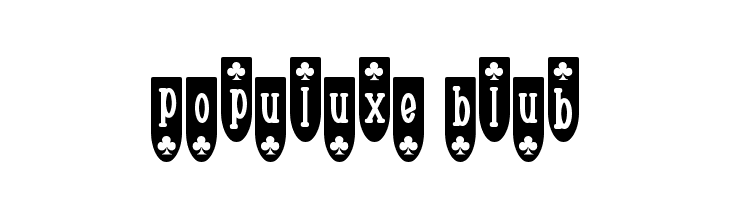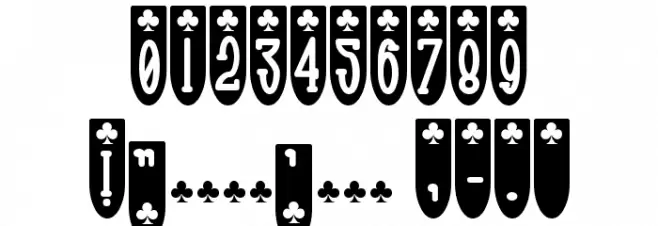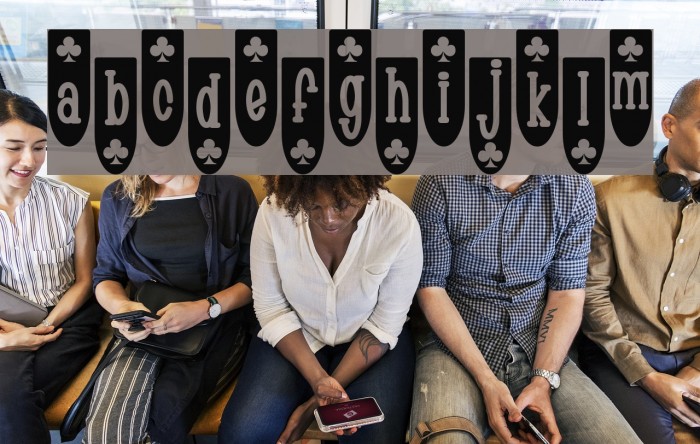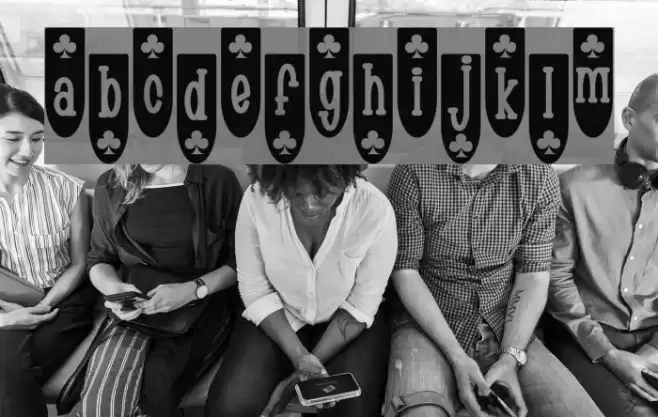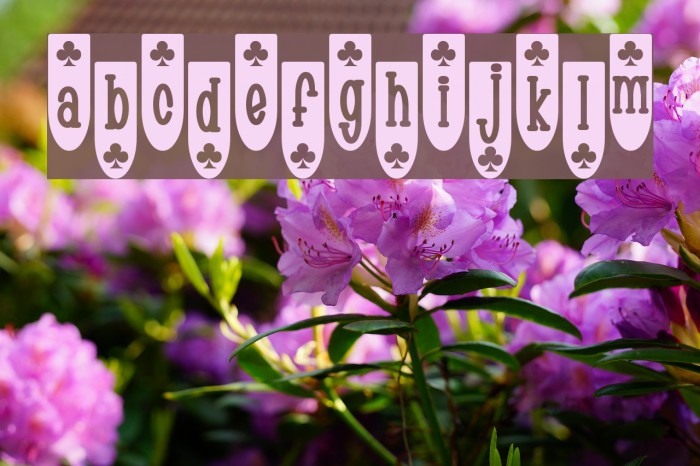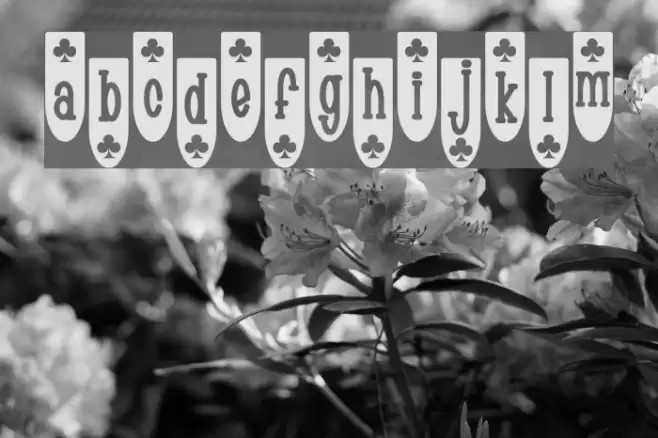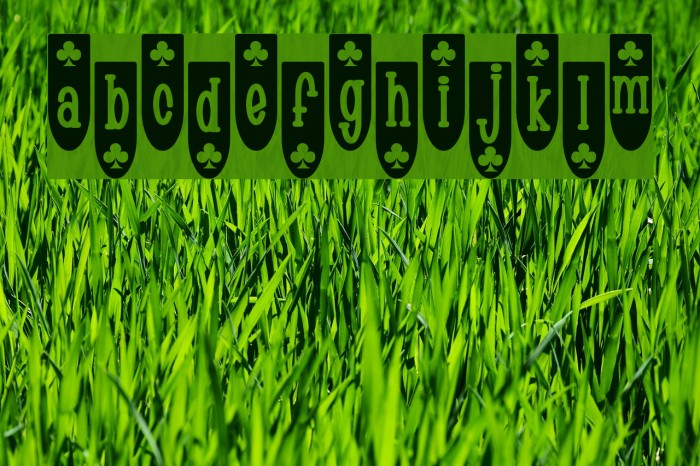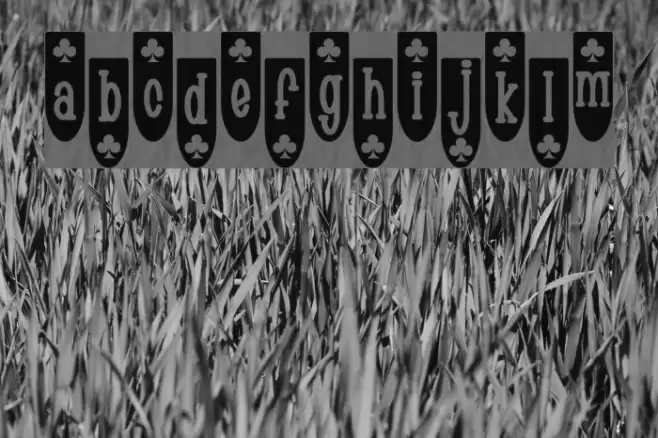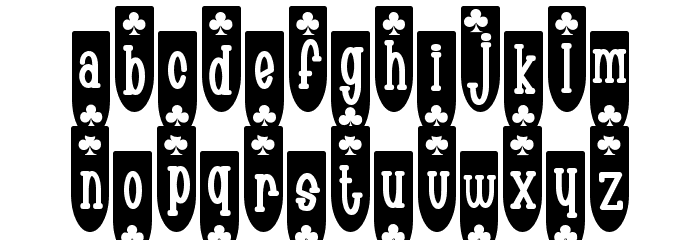
Populuxe Blub Font
| ウェイト | Blub |
| カテゴリ | Images & Symbols |
| 全体的なスタイル | Vintage, Decorative |
| おすすめプロジェクト | Ideal for playful branding, retro-themed posters, children's book covers, and unique invitations. |